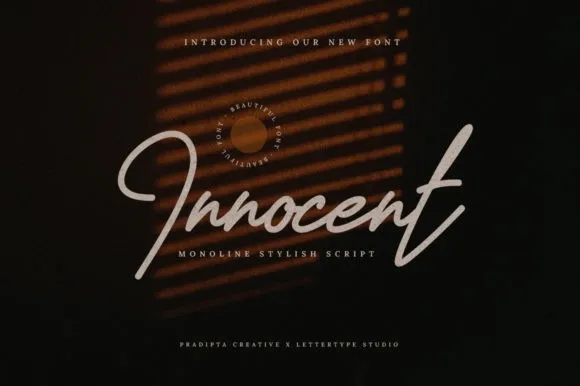
Innocent é uma fonte script criada para oferecer uma sensação acolhedora que remonta ao hábito de escrever a mão com caneta. Esta elegante e revitalizante escolha, feita especialmente para aqueles que buscam um aspecto refinado em seus projetos gráficos, mantém um grau de legibilidade imprescindível. Com sua aparência natural cívrica, esta fonte oferece um toque casual e autêntico a qualquer trabalho que seja apresentado. Para designers buscando uma mudança de look para suas criações, Innocent é perfeito. Ele não apenas mantém o estilo legível e profissional, mas também adiciona um elemento natural que certamente enriquecerá seu design.